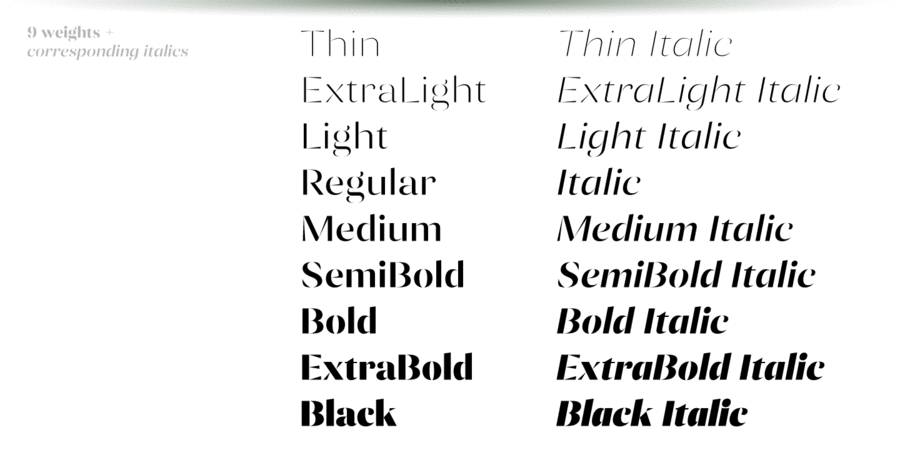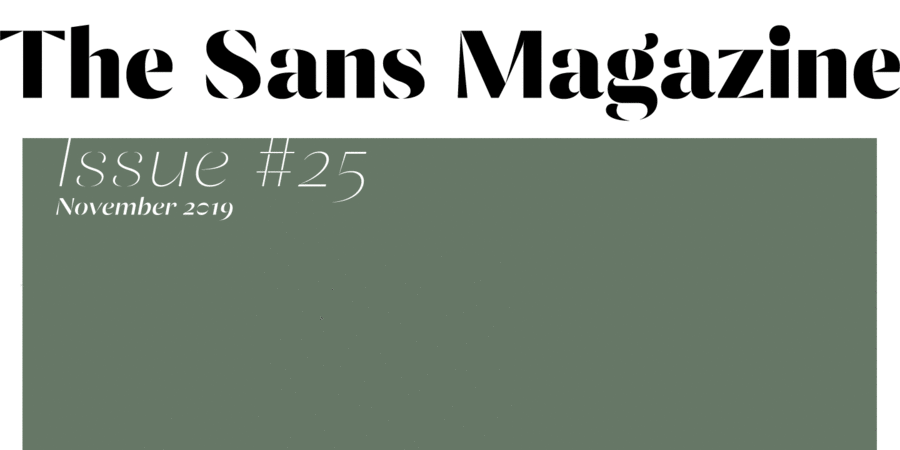
Ponzu – елегантний акцидентний трафаретний шрифт без зарубок. Його форма визначається гострими закінченнями штрихів, які зникають в нескінченному контрасті, наближаючись до основного штриха. Це гібридний шрифт з красивими краплевидними елементами, типовими для антикв. Він ідеально підходить для акцидентного використання в редакційних цілях, для брендингу, постерів, екранних додатків тощо. Ponzu поставляється у 9 насиченостях зі стильним курсивом для кожного прямого накреслення. Підтримує безліч мов, включаючи кирилицю, та має OpenType фічі. Шрифт розробив і випустив Андрій Константинов у студії Mint Type у 2019 році.